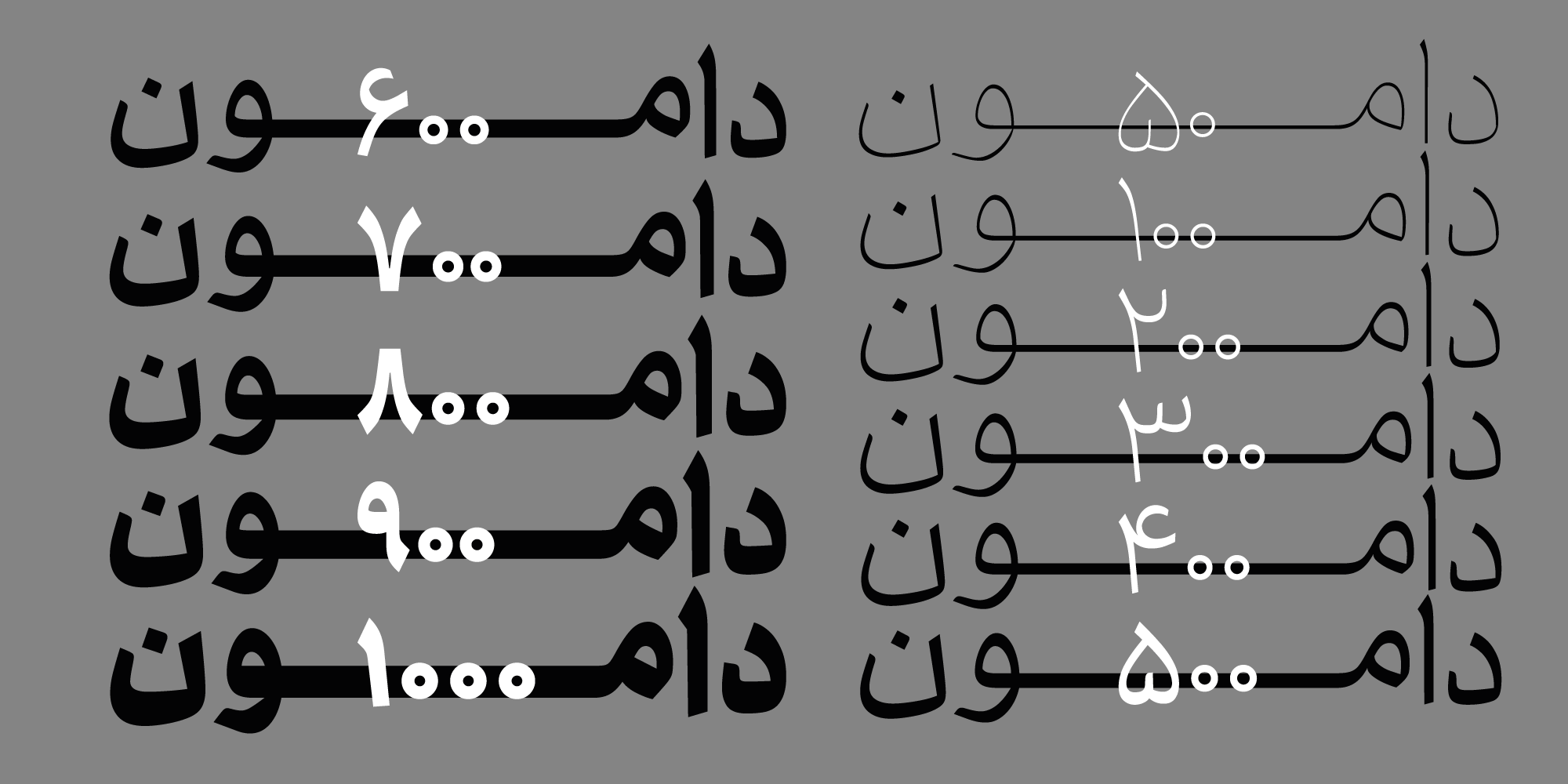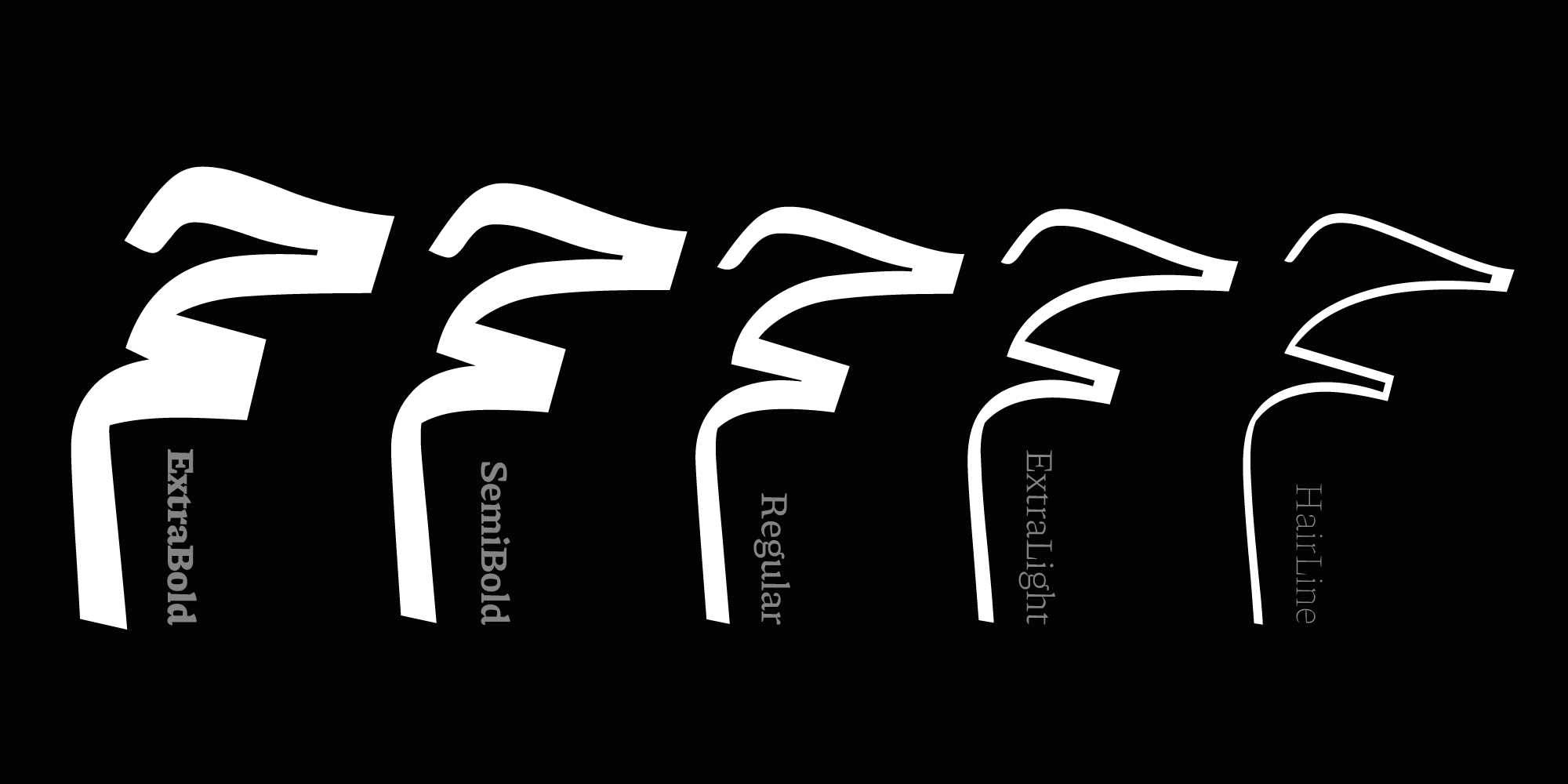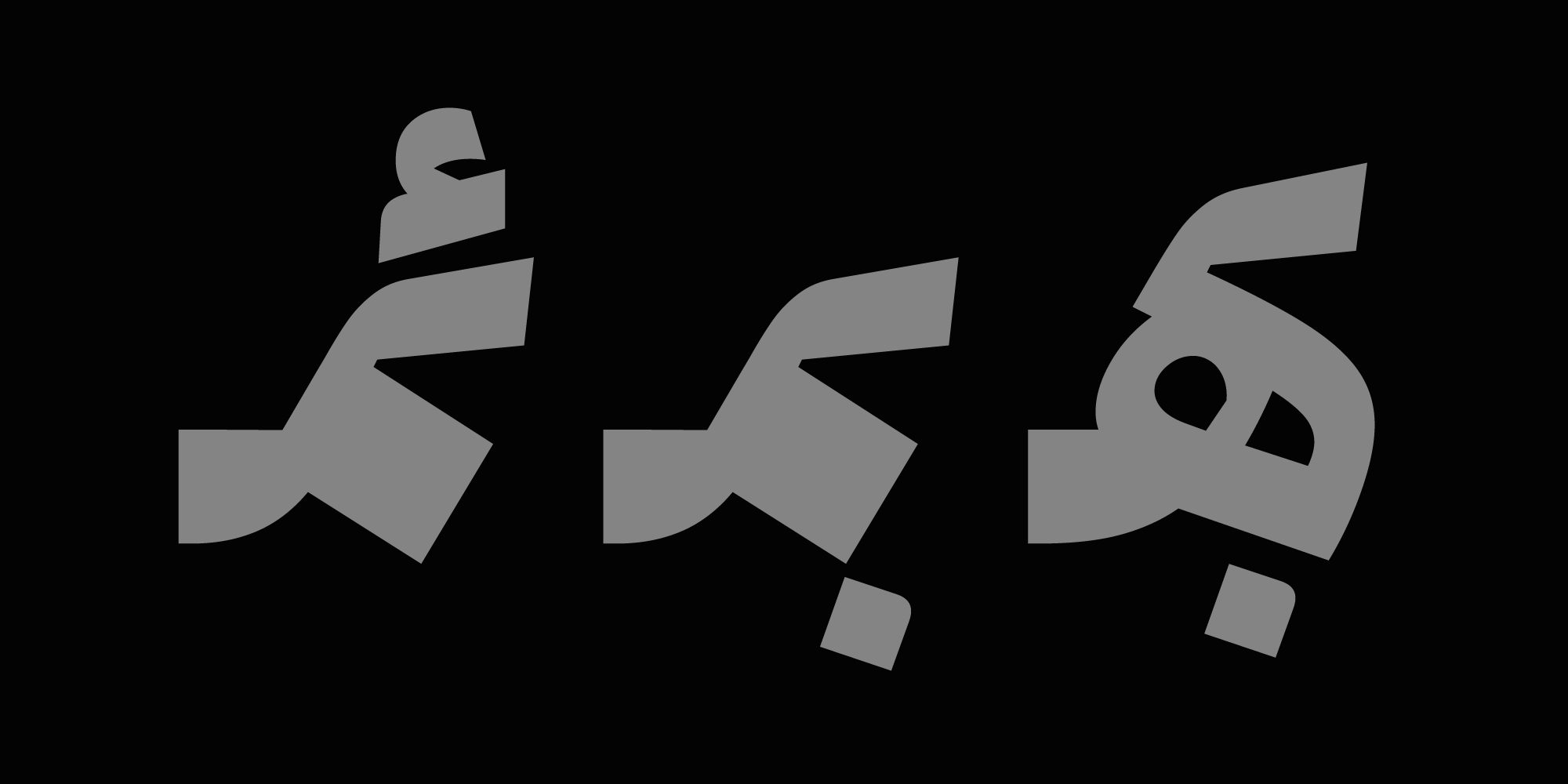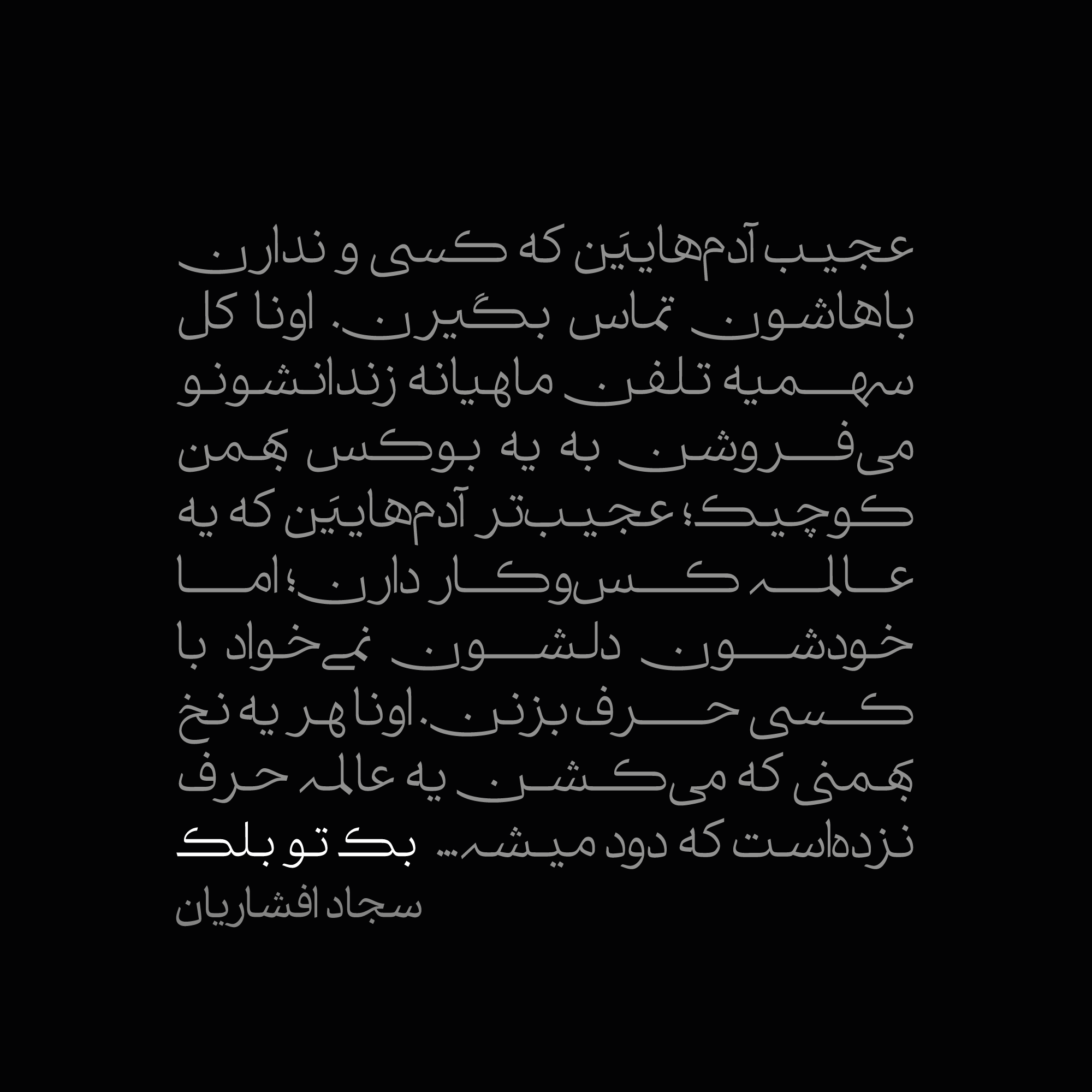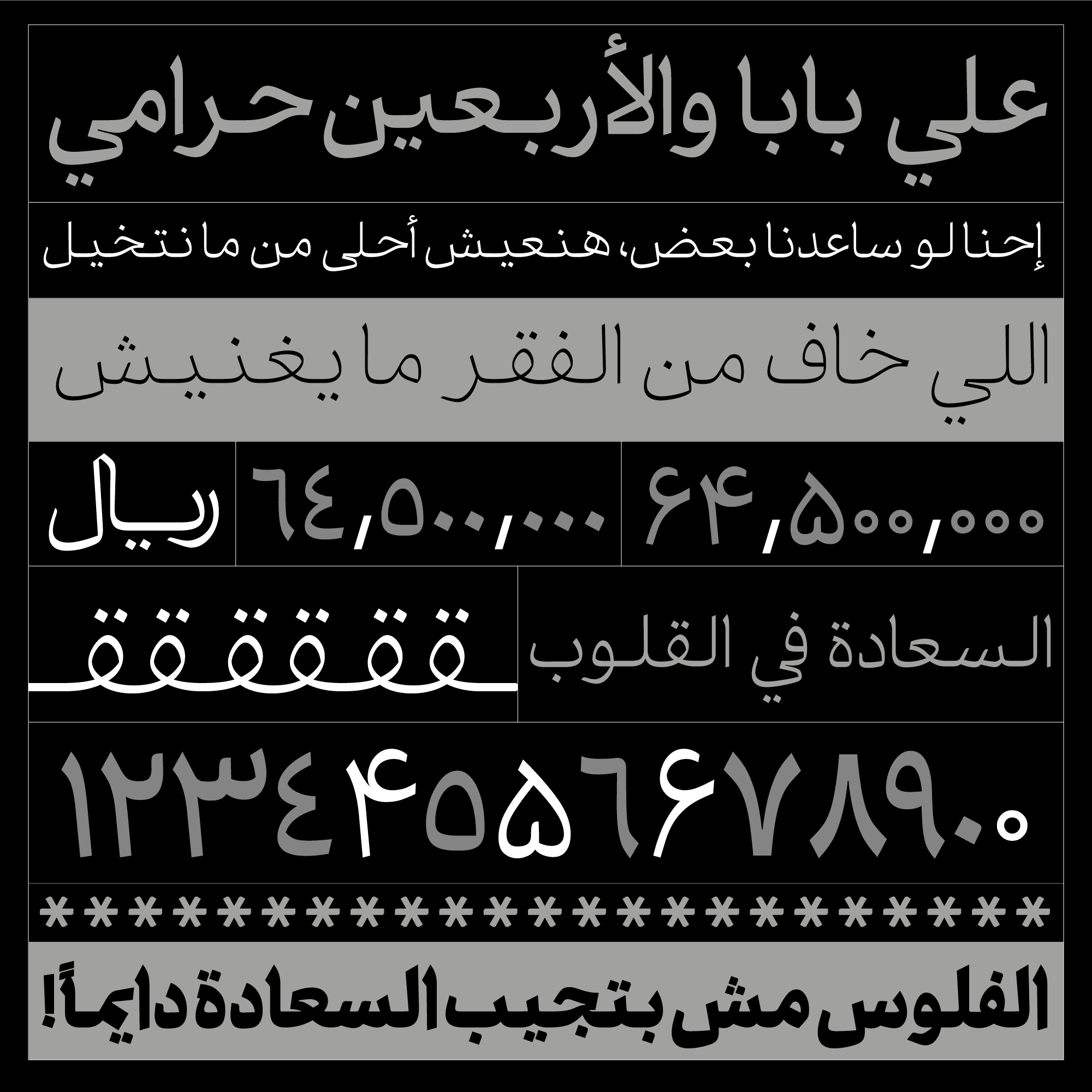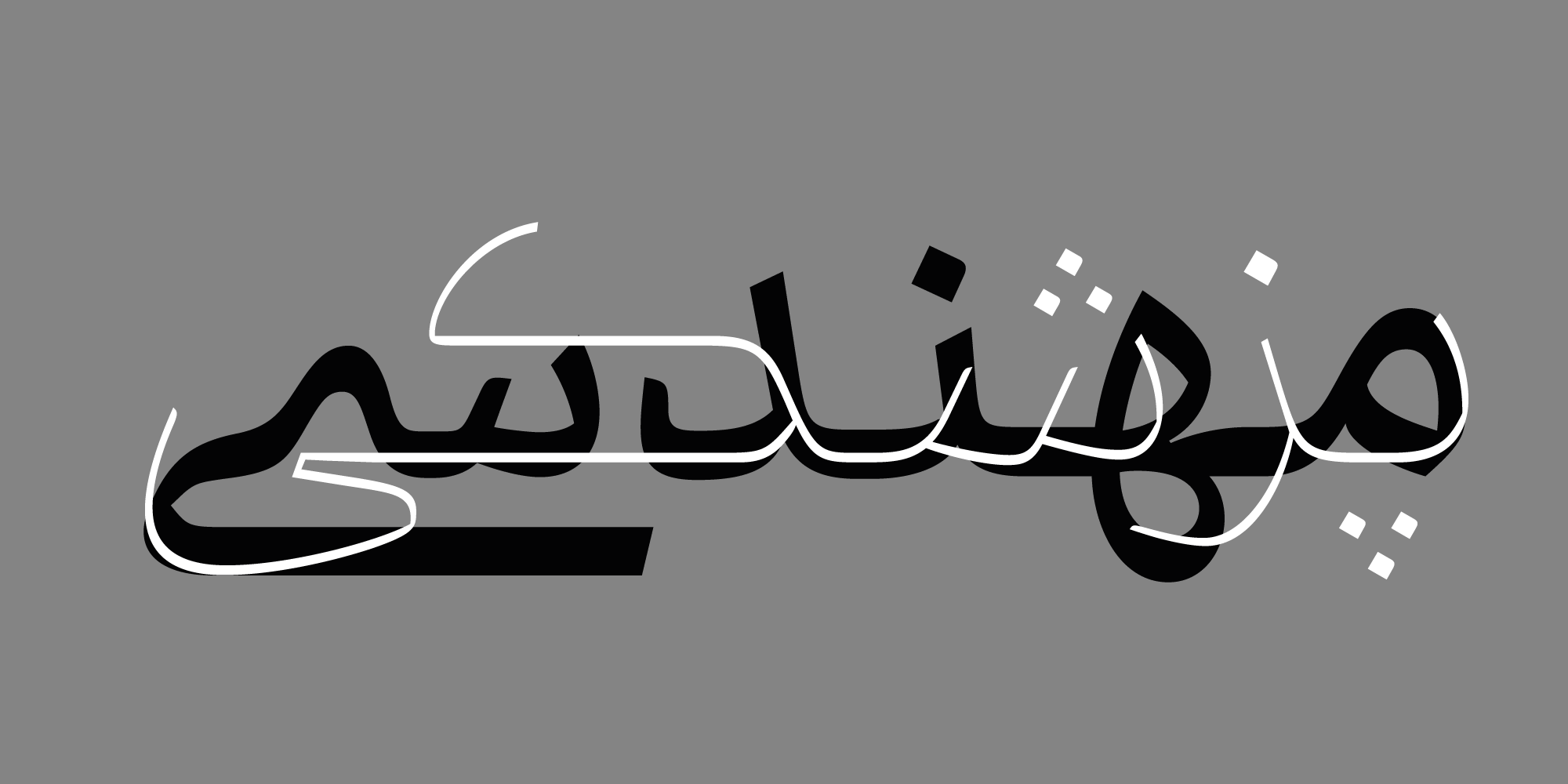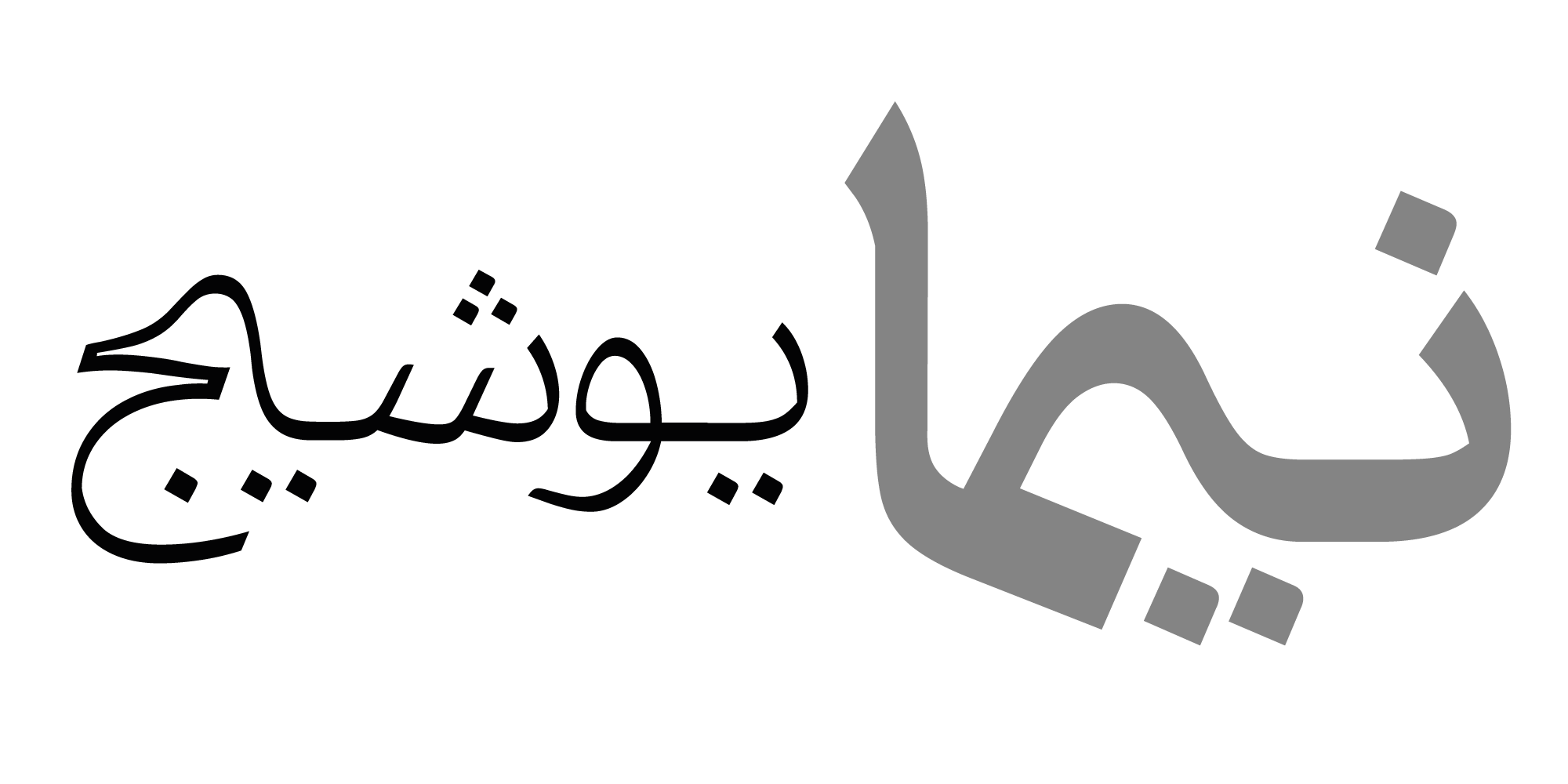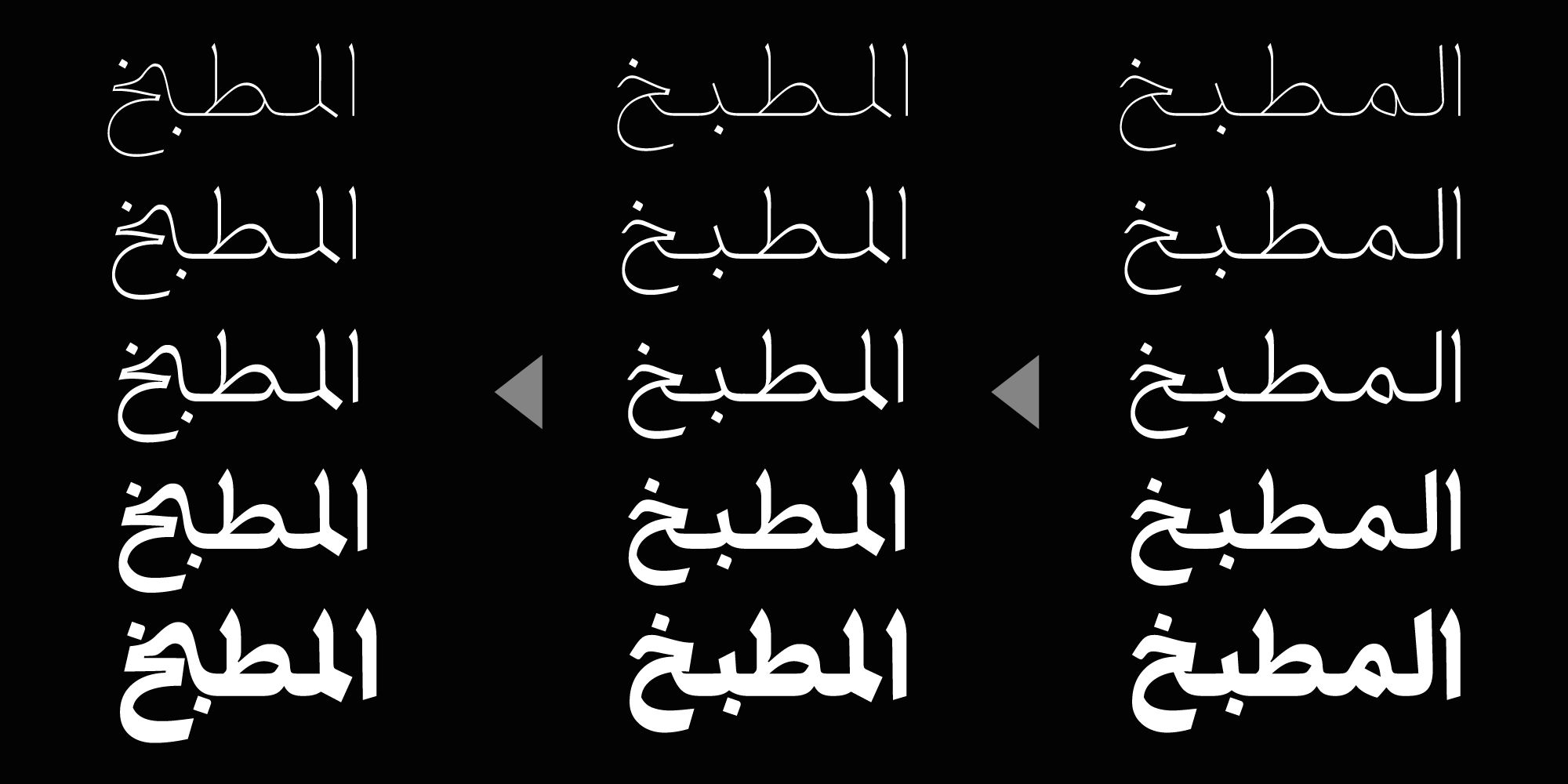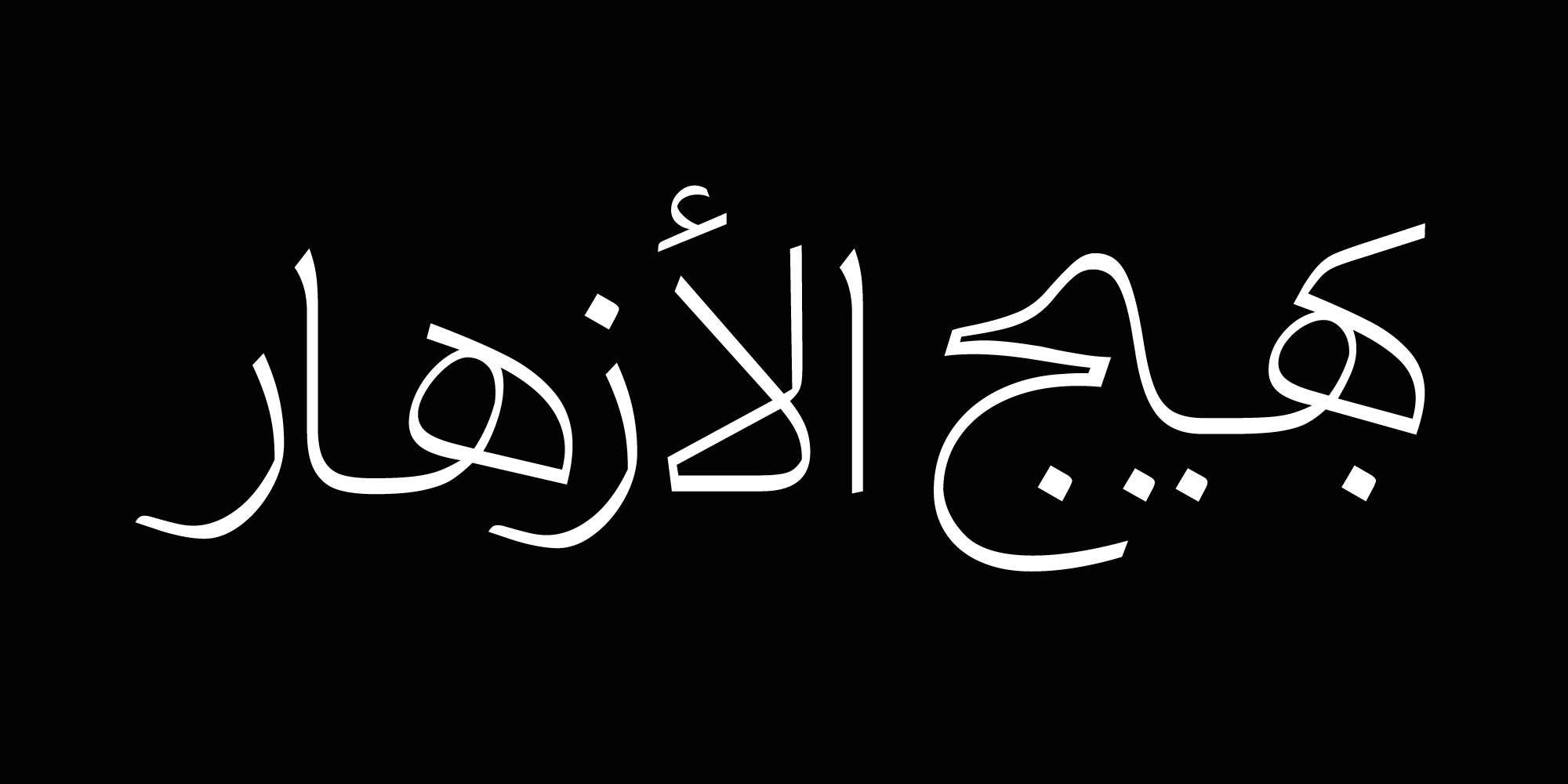
سه نقطهٔ خوشنویسی شده بر پیکر فولادی ساطور قصابی، سرچشمهٔ الهام دامون بود. او با دیدن این همنشینی متناقض، حروفی را آفرید که لطافت و ظرافت خوشنویسی را با برشهای تیز و خطوط جسورانه در هم میآمیزد.
آن سه نقطهٔ نمادین اکنون بر حروفی نشسته که با وجود فرمهای قاطع و مدرنش، سرشار از لطافت و اصالت ایرانی است، گویی در هر حرف، همزمان صدای قلم نی بر کاغذ و ضرباهنگ ساطور بر استخوان شنیده میشود!